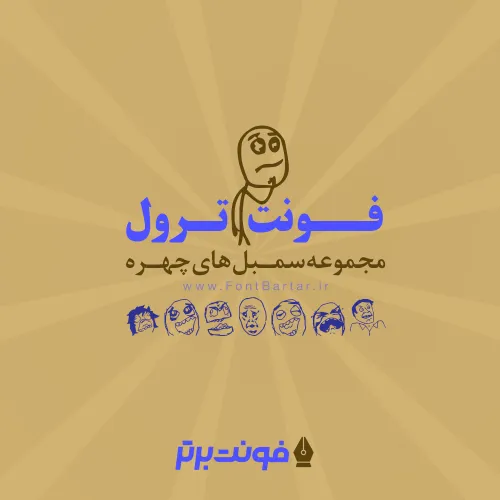
فونت سمبل چهره
فونت ترول ( Far.Chehre ) از سری فونت نماد و شکلک می باشد ، این فونت نماد، شکلک های ترول یا ترل است که در فضای مجازی محبوبیت خاصی دارند.